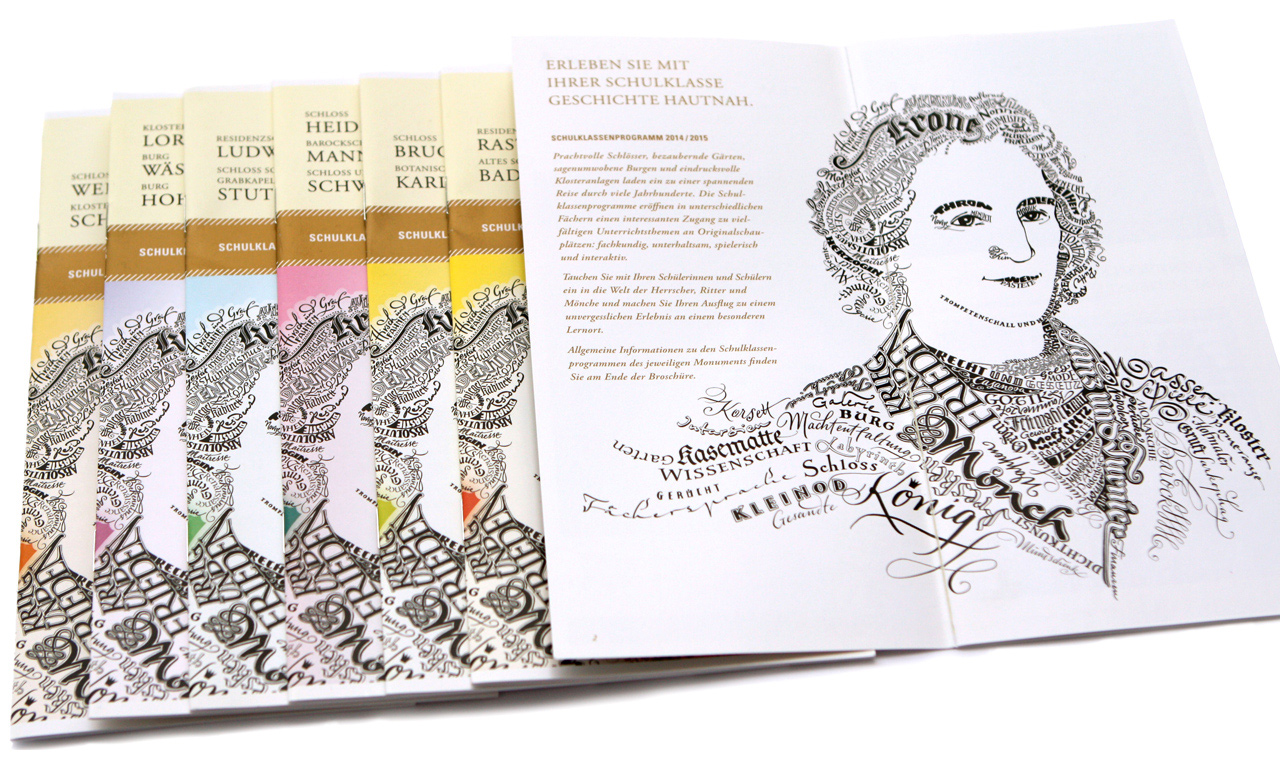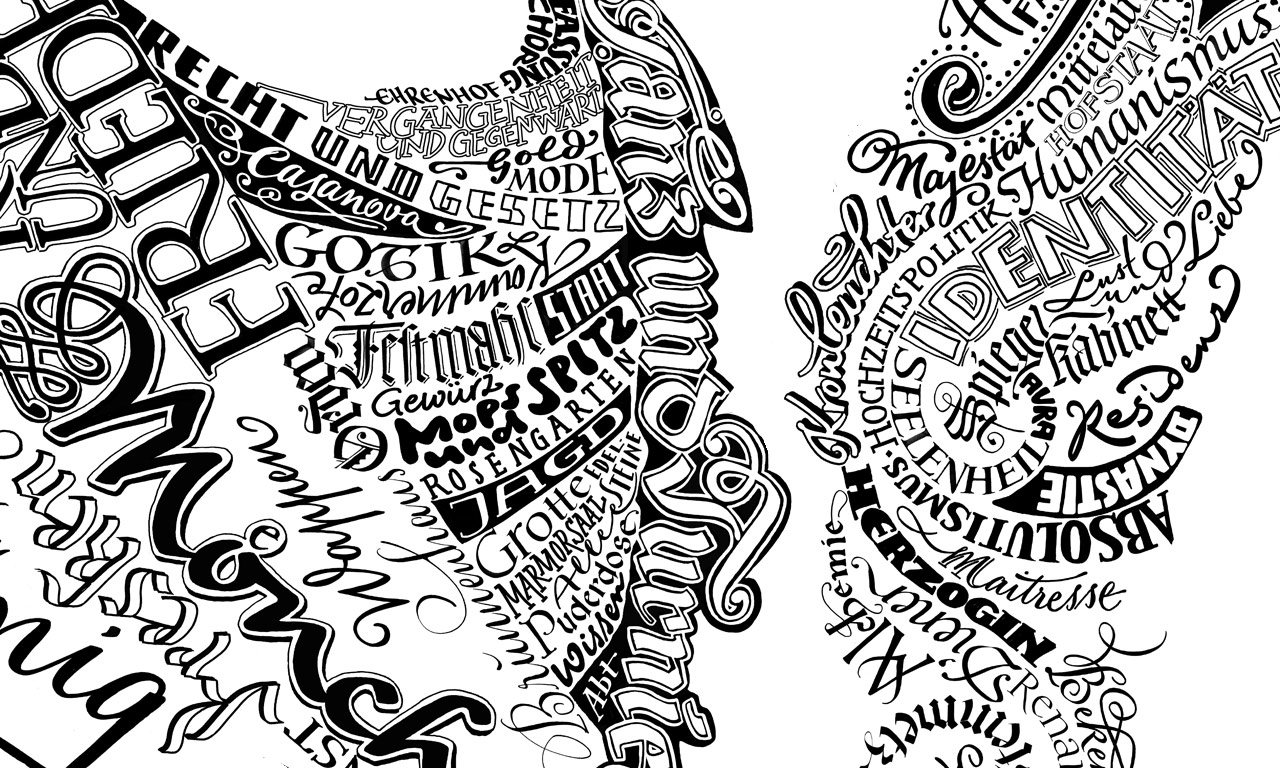
Lettering Portrait
Kalligrafische Illustration. Handlettering, Brushlettering, Kalligrafie, Faux Calligraphy vom Entwurf bis zur Lieferung der Feindaten.
Diese kalligrafische Illustration ist ein Mix aus Kalligrafie, Handlettering, Brushlettering und Faux Calligraphy.
Die besondere Herausforderung des Briefings war, dass die Schrifttypen schriftgeschichtlich zum Inhalt der Worte passen. Da kam mir meine fast 30-jährige Auseinandersetzung mit der Schriftgeschichte aus den unterschiedlichsten Jahrhunderten in Theorie und Praxis sehr entgegen.